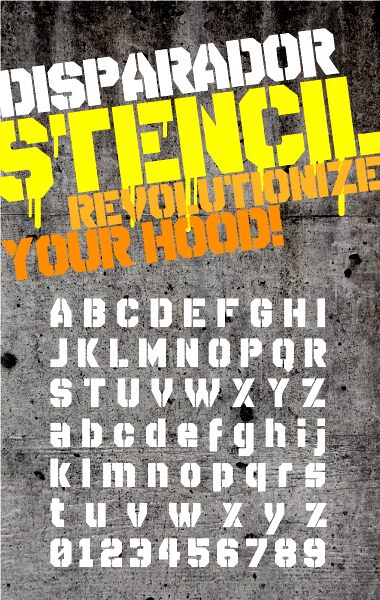
Disparador Stencil von Tobias Sommer ist eine kostenlose Techno-Stencil-Display-Schrift, die aus quadratischen Formen und scharf geschnittenen Verbindungen aufgebaut ist. Breite Striche, schmale Brüche und abgestufte Ecken verleihen dem Schriftbild das Aussehen segmentierter Maschinen oder eines robusten Bedienfelds. Seine kompakte Silhouette wirkt kraftvoll und kontrolliert.
Die blockhafte Konstruktion kann an Schnittstellenpaneele, technische Diagramme und hartkantige Illustrationen erinnern, was sie nützlich für Spielegrafiken, Plakate für elektronische Musik und Science-Fiction-Publikationen macht. Auf Elektronikverpackungen oder Merchandising im taktischen Stil können die wiederkehrenden Schablonenlücken Teil des Markensystems werden und sich in Icons, Rändern und Produktkennzeichnungen über eine gesamte Produktpalette hinweg wiederholen.